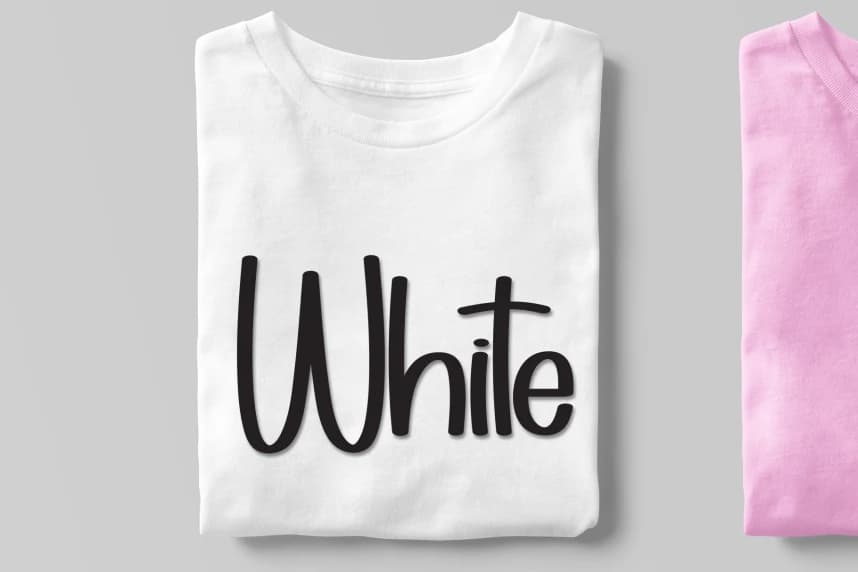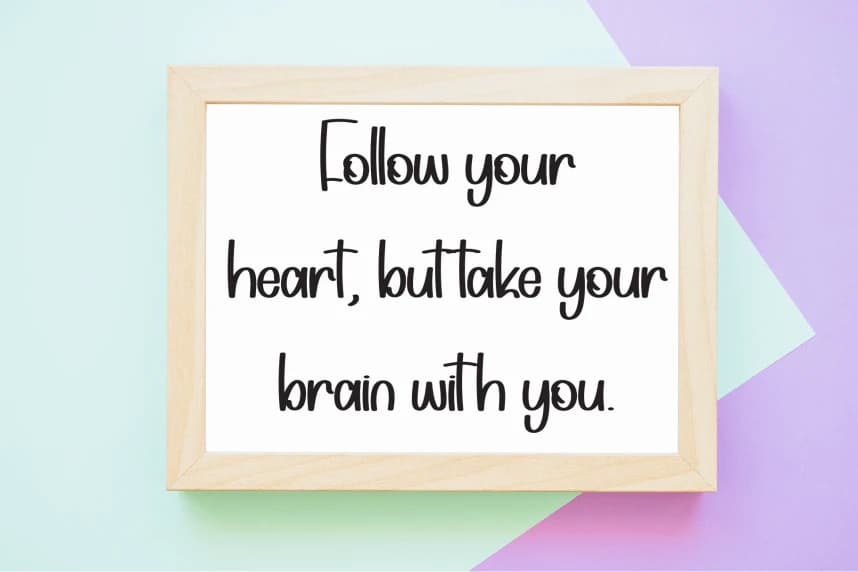
Sweetie – Modern ve Benzersiz Yazı Tipi
Sweetie – Moder And Unique Font, tatlı ve samimi bir el yazısı gösterim yazı tipidir. Sevimli ve eğlenceli; bu yazı tipi düğün davetiyeleri, kartlar veya oyun tadında bir dokunuşa ihtiyaç duyabilecek herhangi bir tasarım için idealdir.
Sweetie – Moder And Unique Font, tatlı ve samimi bir el yazısı gösterim fontudur. Sevimli ve eğlenceli olan bu font, düğün davetiyeleri, kartlar veya oyuncu bir dokunuşa ihtiyaç duyabilecek diğer tasarımlar için idealdir.